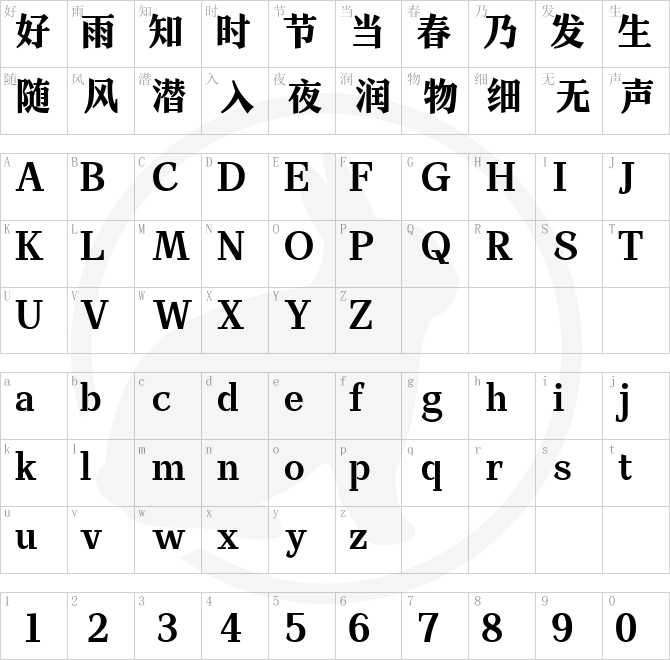
YEFONTShanHaiMingChao
YEFONTShanHaiMingChao,这款字体结构工整、笔画清晰,兼顾美观与易读性,适用于标题、正文、海报、包装、LOGO 等多种场景。字形优雅稳定,风格百搭耐看,适配日常排版与创意设计,让文字呈现更舒适、更具质感。YEFONTShanHaiMingChao一笔一画,皆是细节,以均衡的比例、流畅的线条打造舒适视觉体验,字形端正大气,风格简约现代。无论是商业设计、品牌宣传还是日常排版,都能轻松驾驭,让文字更有格调与力量。YEFONTShanHaiMingChao字体下载。